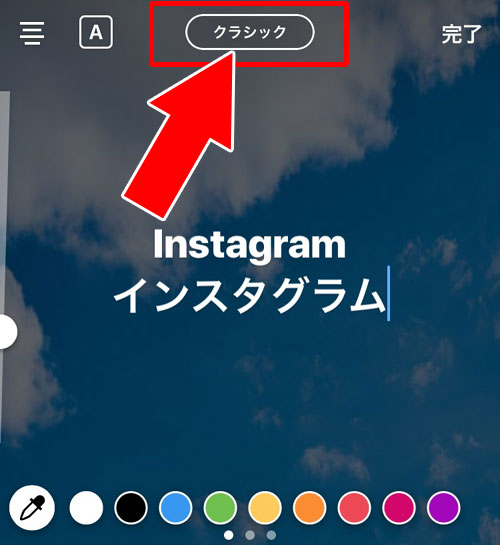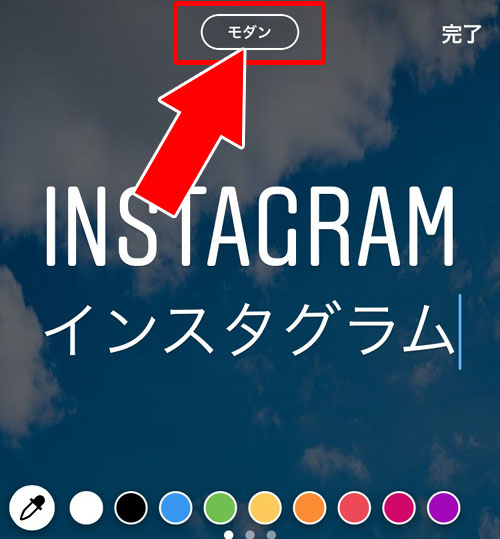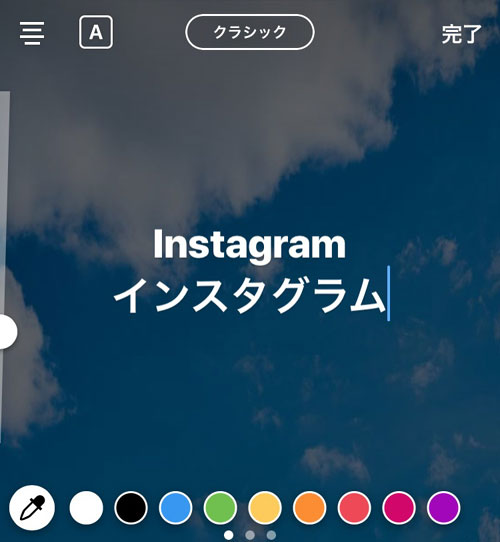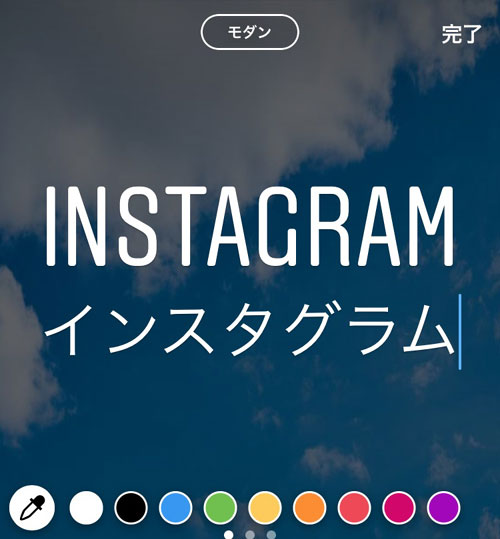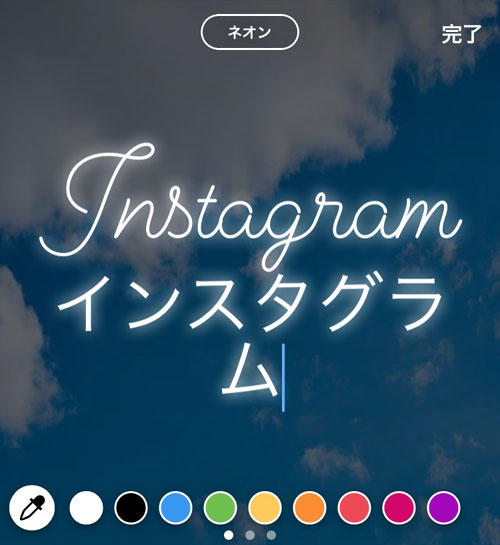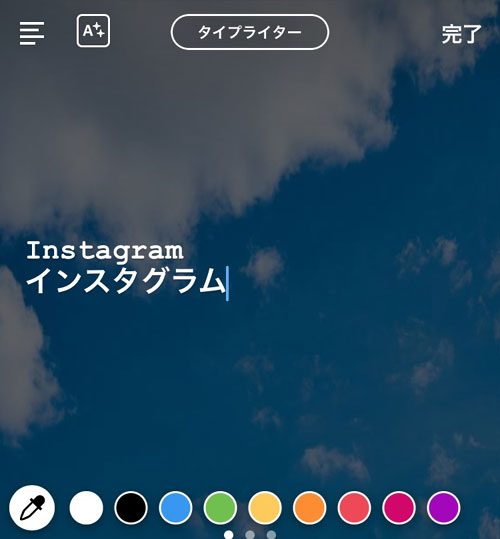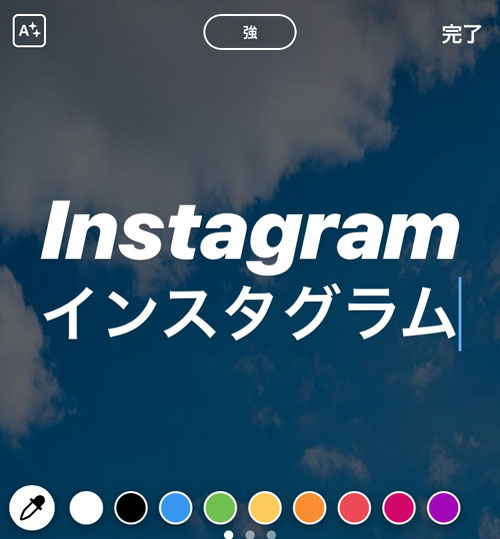
インスタで文字の字体を変える方法!名前やプロフィールのフォントも可愛く変更
インスタグラムで文字の字体を変える方法があるのをご存知ですか?
ストーリーだと『タイプモード』という機能や文字編集画面で英語フォントを筆記体やネオン文字などに変更したりもできます。
フォントを変更するだけでストーリーの印象も変わりますよね。
また、ストーリーだけでなくキャプションや名前などプロフィールのフォントを変える方法もあります。
文字の字体を変えると聞くと専用のアプリをダウンロードしたりするイメージがありますが、今回まとめたのはアプリのダウンロードなどは必要ないやり方です。
このページではインスタで使える文字とコピペして利用する文字の使い方について解説します。
普段とは少し違うフォントを使って投稿したりストーリーのフォントを変えたい方の為にインスタで文字の字体を変える方法についてまとめたので参考にして下さい。
インスタで文字の字体を変更できる箇所
インスタで文字の字体を変更できる箇所は以下の3箇所になります。
• インスタストーリー
• プロフィール(名前、自己紹介)
• キャプション
これらの場所で文字を書くことができますが、その時に使用する文字を通常とは違う字体に変更する事ができます。
字体の変更方法はストーリーとプロフィールで変え方が違います。
以下でそれぞれのやり方について詳しく解説します。
ストーリーの文字を変更する
インスタストーリーで使用する文字の字体を変更する一番簡単で基本的な方法は、写真を編集する画面で文字を入力した後にフォント変更するやり方です。
具体的な方法については以下になります。
1. インスタグラムアプリを起動し、ストーリー画面を開く
2. ストーリーの写真を撮影、またはカメラロールから写真を選択し、ストーリー編集画面の右上にある『Aa』をタップ
4. 好きな文字を入力
6. 文字を入力後に画面上部の『クラシック』をタップ
8. 何度もタップするとフォントが変更されます
これでストーリーで入力した文字の字体を変更する事ができます。
ストーリーで変更できる文字の種類
ストーリーで変更できる文字は現在5種類あります。
クラシック
モダン
ネオン
タイプライター
強
基本的に日本語ではあまり文字の違いはわかりませんが、英語(アルファベット)にすると字体の違いが一目瞭然です。
フォントの種類に関しては今後増える可能性もありますね。
プロフィール(名前と自己紹介)の文字を変更する
インスタのプロフィール(名前と自己紹介)の文字を変更する事もできます。
プロフィールの文字の字体変更はストーリーのように予め字体が用意されているわけではありません。
そこで、使うのが特殊文字と言われる文字です。
例えば、以下のような文字が特殊文字と言われてます。
特殊文字とは通常では変換できないような文字の事で、一般的には専用ツールやアプリを使ってコピペして利用します。
インスタの名前や自己紹介で変わった字体の文字が表示されている場合は特殊文字を使っている状態です。
特殊文字を使いたい時は以下のツールを使うと簡単です。
ツールの使い方としてはカテゴリを選択してコピペしたい文字のボタンをタップするだけなのですぐに利用できます。
ツールを使ってコピーした特殊文字をインスタの名前や自己紹介部分に貼り付けて保存すれば以下のように普段とは違う文字の字体でプロフィールを表示させる事ができます。
キャプションの文字を変更する
キャプションの文字の字体を変更するやり方はプロフィールの変更方法と同じです。
基本的には文字の字体を変更する為の特殊文字をコピペして利用するといった感じですね。
キャプションの文字を変更する際に注意すべきなのは、特殊文字をハッシュタグにしない事です。
特殊文字はハッシュタグとして利用できない文字も多いです。
せっかくコピペして可愛い字体に変更してもハッシュタグとしての効果がつかない可能性があるので、ハッシュタグとして利用するのはおすすめできません。
ハッシュタグは通常の文字を使うようにして、それ以外の部分で字体を変えた特殊文字を使うようにすると良いでしょう。
特殊文字はストーリーでも使える
ストーリーで文字の字体を変えるには最初に解説した方法で変更できますが、実は特殊文字もストーリーで使う事ができます。
特殊文字をストーリーで使うと以下のような感じになります。
元々ストーリーで用意されたフォント以外でストーリーの文字を変えたい時には特殊文字を使うのが良いですね。
ストーリーに貼り付けた文字は色変えや大きさ変更などの加工をして投稿できます。
見たことないような字体の文字をストーリーで見つけた場合には特殊文字を使ってフォントの変更を行っているという事なので覚えておくと良いでしょう。
フォントは今後も増えることに期待
インスタでは写真や動画を中心として人気が広がっていますが、写真や動画とセットで文字も書くことが多いです。
ストーリーで動画に文字を加工したり、通常投稿のキャプションで写真のコメントを入れたりしますよね。
文字を入れる時にはフォントが重要になり、フォントを変えると可愛さもオシャレさも変わってきます。また、インスタのタイプモードのように文字だけを入力して投稿するというケースも増えてきました。
このことから、文字やフォントは今後も増える事が期待できます。
フォントが増えるとそれだけで楽しめる要素が増えるので嬉しいですね。また新しいフォントが使えるようになったりしたら当サイトでお知らせしたいと思います。